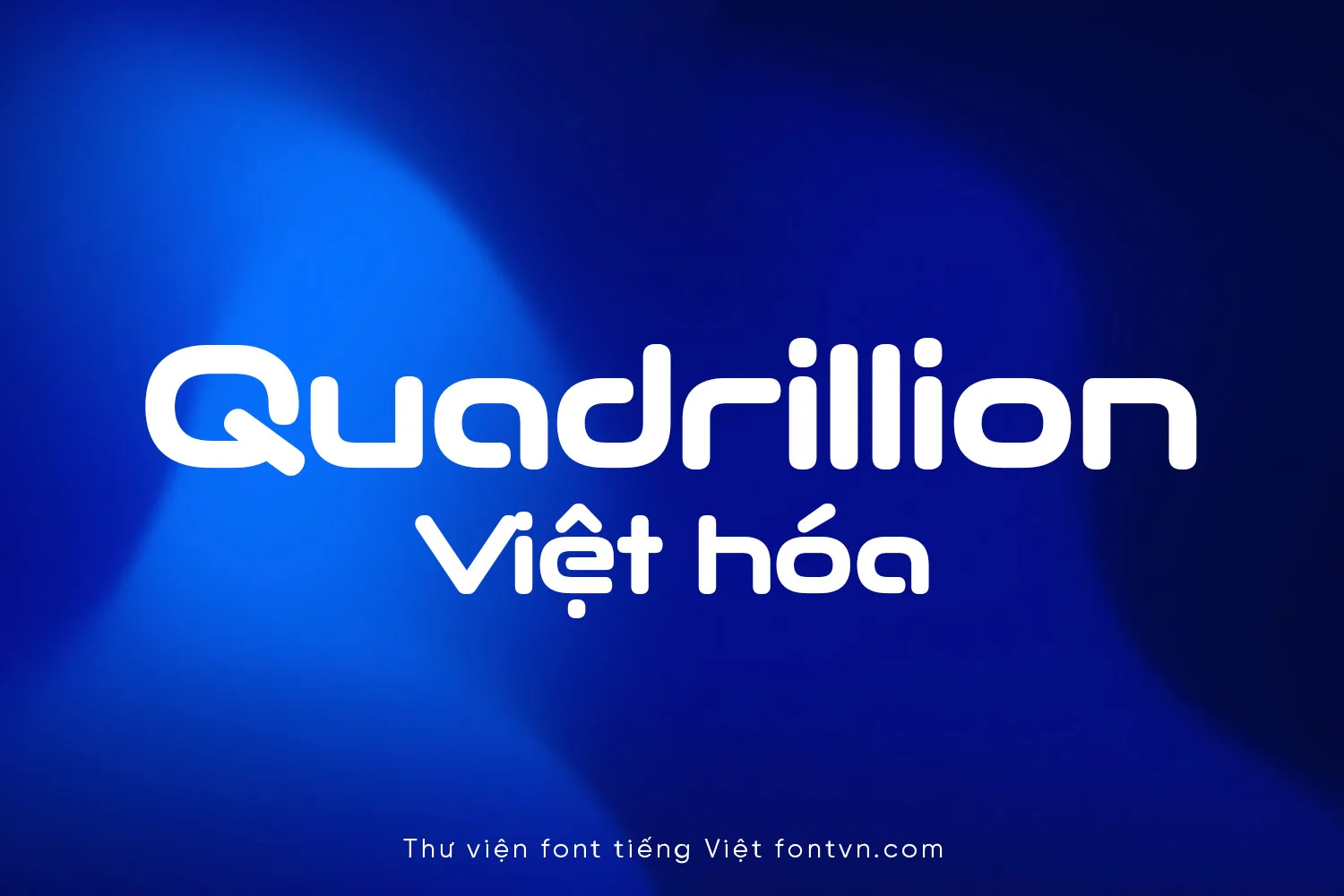
DVN Quadrillion Việt hóa – Font khoa học công nghệ tuyệt đẹp [2 Font]
Quadrillion mang đậm phong cách “Corporate Hypermodern”, là sự kết hợp hoàn hảo giữa cấu trúc hình học chính xác và hơi thở của tương lai. Điểm nhấn của kiểu chữ này nằm ở dáng chữ rộng đặc trưng (wide stance) cùng các ký tự dạng viên nang (capsule-like) có phần đầu nét bo tròn mềm mại. Cấu trúc này tạo ra một hiệu ứng thị giác “nhựa” (plastic presence) độc đáo, giúp font chữ vừa toát lên vẻ táo bạo, hiện đại của công nghệ cao, lại vừa giữ được sự thân thiện, sang trọng và đảm bảo khả năng đọc hiểu (readability) tuyệt vời.